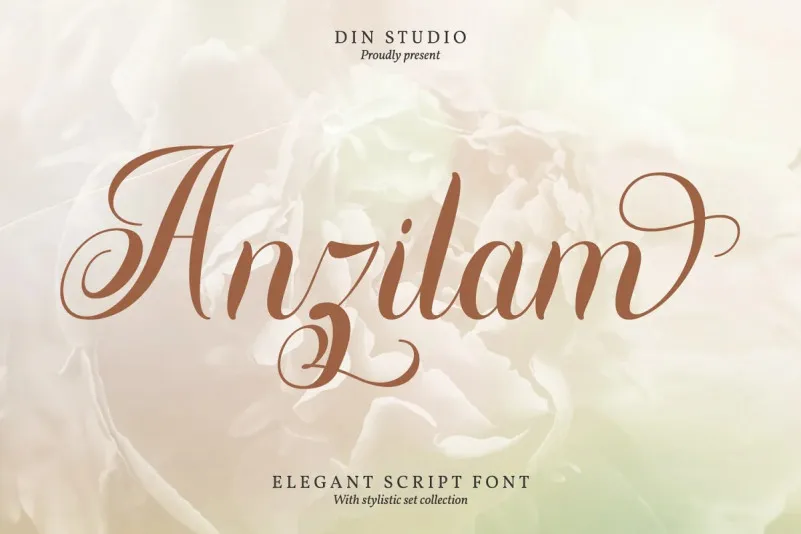
Anzilam Calligraphy Font – Fonte Grátis
Anzilam Calligraphy Font
Anzilam Calligraphy Font é uma elegante e sofisticada fonte de escrita que combina a sofisticação do estilo clássico com a beleza moderna. Criada pela Din Studio, esta fonte de script está disponível para qualquer projeto profissional que desejou adicionar um toque refinado e distintivo à sua identidade visual. Perfeita tanto para criar logos ou marcas como para o design de branding, ela também se destaca em aplicações mais pessoais como cartões de aniversário ou mensagens de casamento. A Anzilam Calligraphy Font é uma escolha perfeita para quem procura um estilo que combine elegância e sofisticação sem abrir mão do charme de uma tipografia tradicional. Uma excelente fonte para quem busca adicionar um elemento único e pessoal a seus projetos visuais, seja para um evento especial ou apenas para melhorar a identidade visual de sua marca.